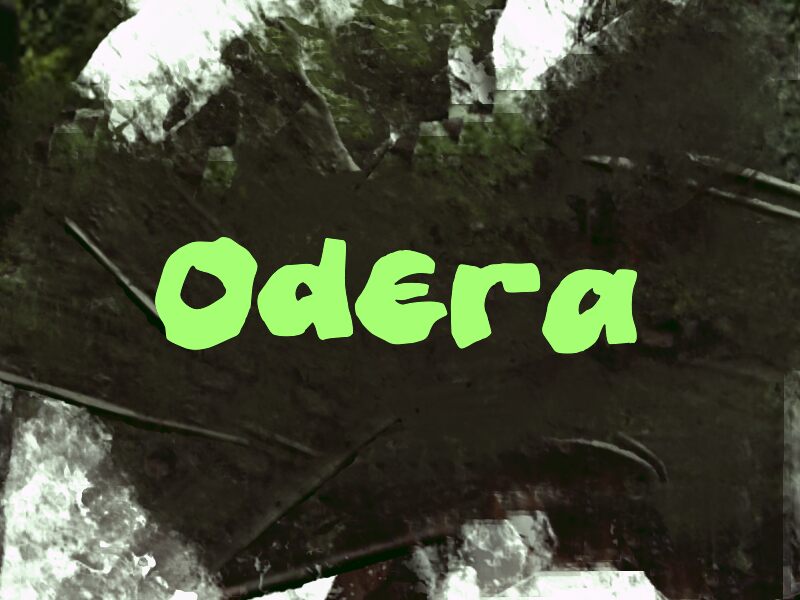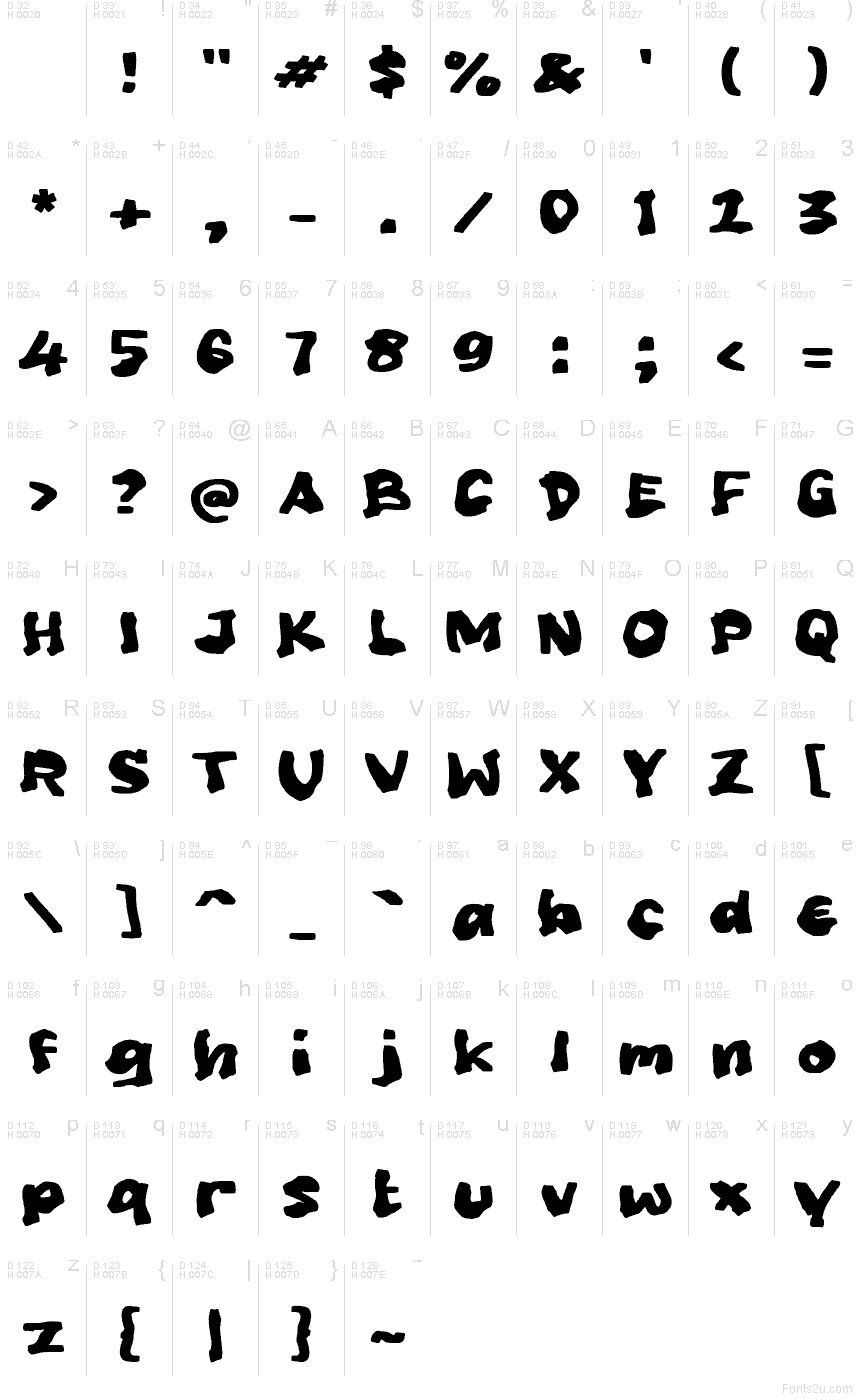
Odera
Odera od Wep je bezplatné písmo v štýle graffiti s nafúknutými, nepravidelnými siluetami, ktoré vyzerajú, akoby boli vytvarované z mokrej farby namiesto kreslenia podľa mriežky. Zaoblená hmota a otlačené hrany dodávajú znakom uvoľnený pouličný nádych, zatiaľ čo otvorené vnútro písmen bráni tomu, aby font pôsobil ako plochý bublinový štýl.
Plagáty, obaly albumov, skate grafika, letáky či návrhy nálepiek – tam všade Odera vynikne, najmä ak potrebujete, aby nadpis pôsobil drsne a ručne kreslene namiesto uhladených tvarov. Vďaka nepravidelným kontúram a kompaktnej vizuálnej váhe dodáva Odera krátkym nadpisom, štítkom na tovare aj príspevkom na sociálnych sieťach autentickú energiu graffiti, bez potreby spoliehať sa na efekt stekajúcej farby alebo iné zbytočné úpravy.